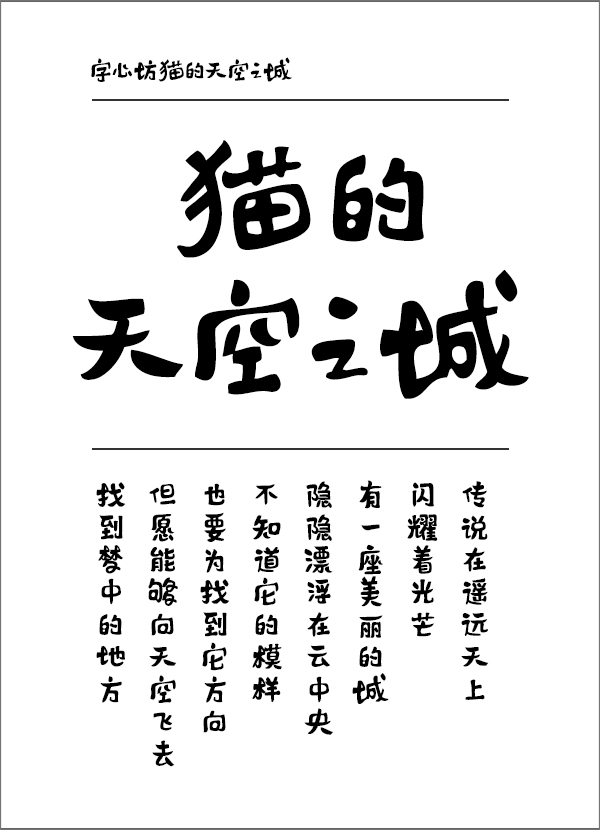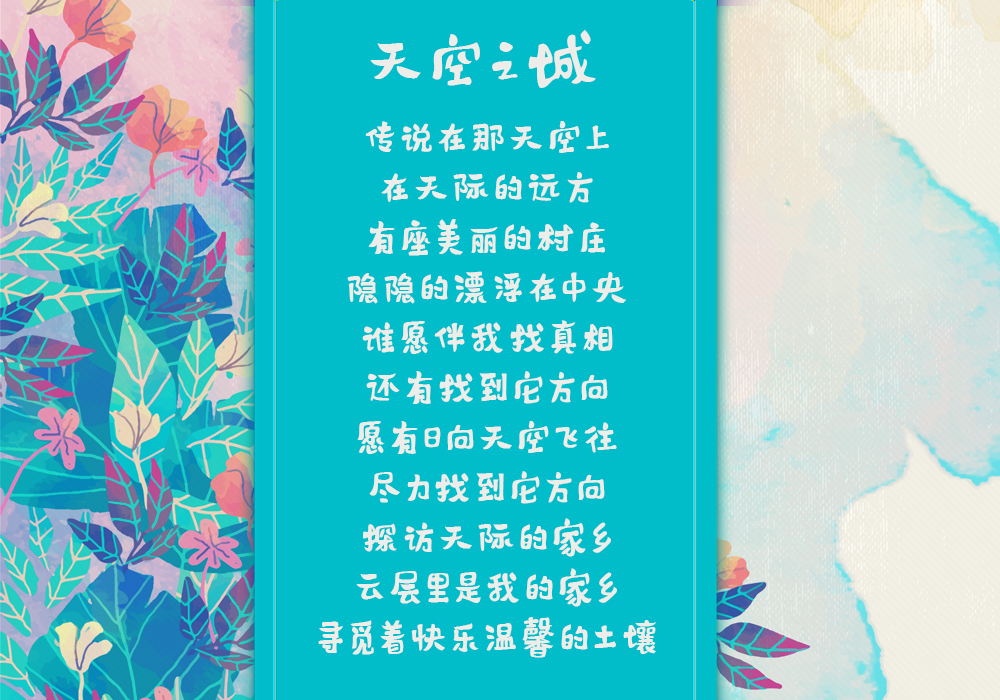
字心坊猫的天空之城
该字体由字心坊为猫的天空之城特殊定制。字心坊基于猫的天空之城LOGO的设计风格,运用猫空的设计元素逐一设计出符合国家GB2312-80字符集标准的6763个字形,最后编译出整套字库。字体风格文艺、新颖、可爱、卡通、小清新。
字体风格:文艺 / 小清新 / 卡通 /可爱/ 时尚
推荐场景: 标志 / 导视 / 书籍 / 游戏 / 动漫 / 影视 / 屏显